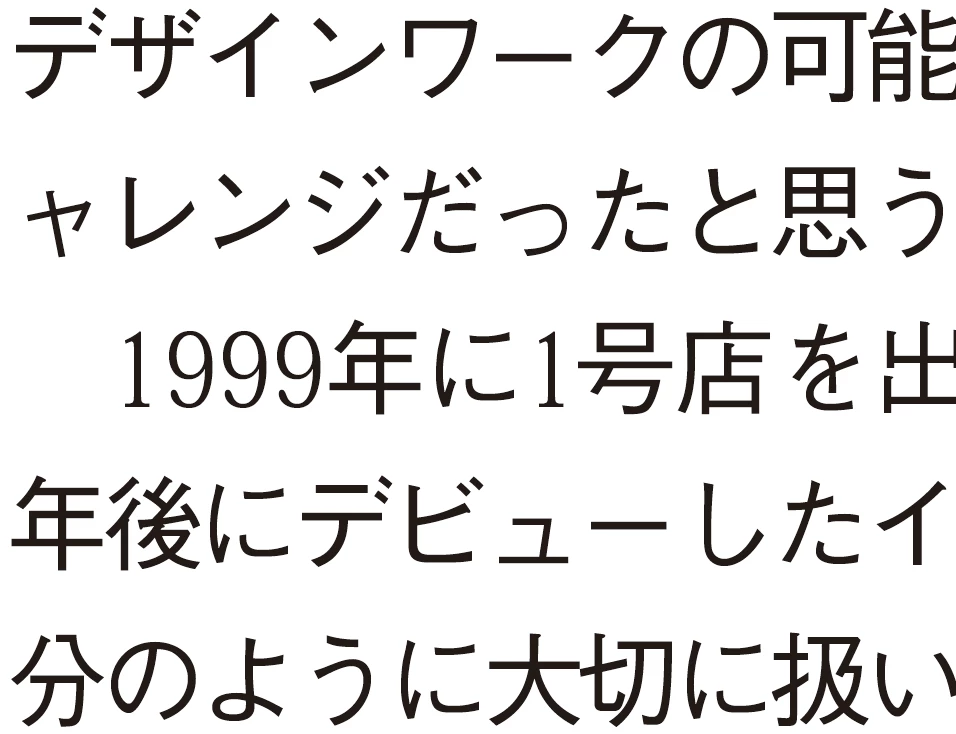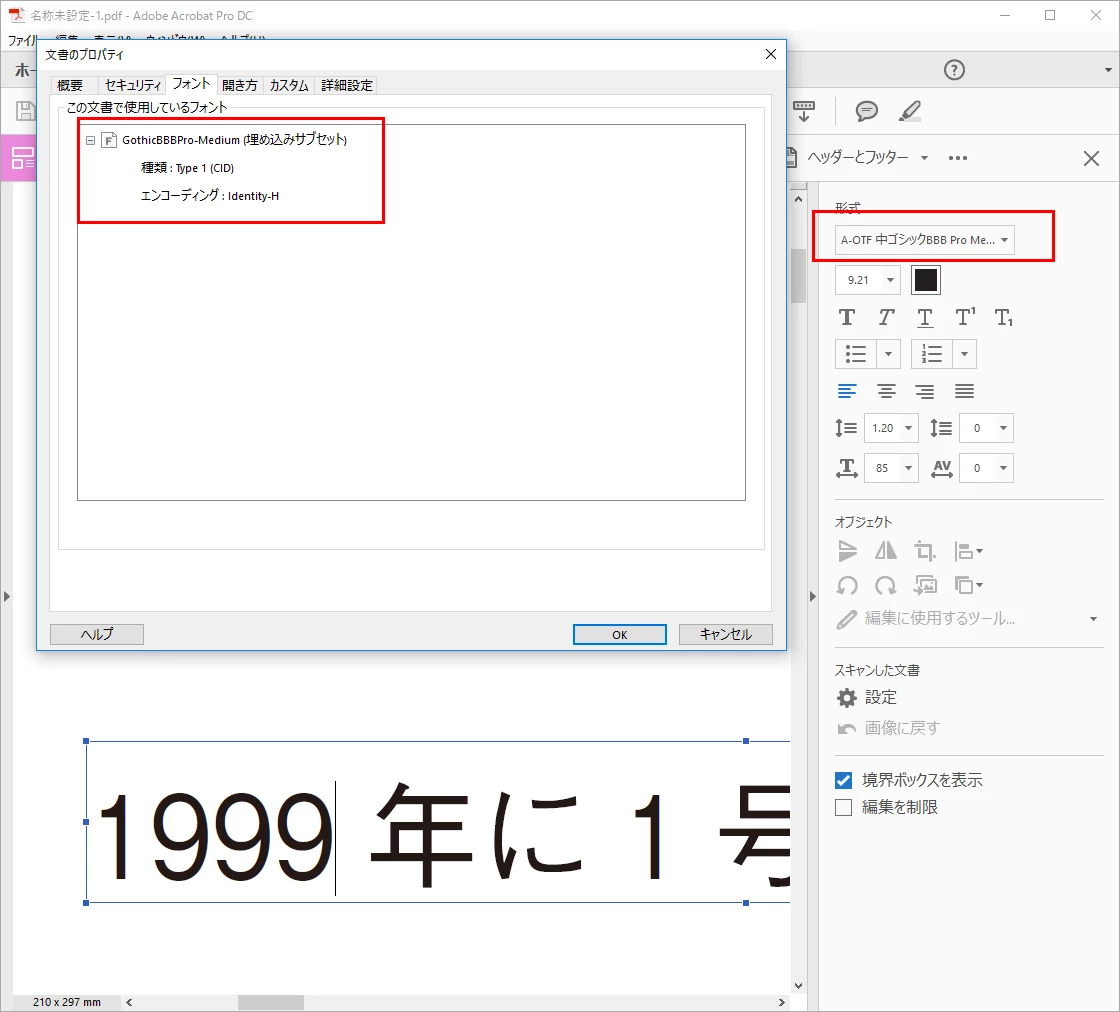
InDesignCS6でPDFを書き出した際に合成フォントが化ける
InDesignCS6(8.0.2)でPDFを書き出した際に合成フォントを使用している箇所で数字の部分だけが文字が化けました。
そういった現象は起きるのでしょうか?
フォントの確認ですが、こちらはAcrobatで行った場合、という話になります。
PDFのプロパティやPDF編集(TouchUp)等で見た場合の、該当部分のフォントはどうでしょうか。
ただ、簡単にですが同様の設定を作って試した限りは再現しませんでした(CS6 8.1)。
また別口の考えなんですが、プロポーショナル字形の85%変形を使う理由がわかりません。
それだけ変形を行うとバランスが悪くなると考えるためです。
もし幅を狭くしたいということであれば、別のコンデンス系欧文フォントを用いるなどであったり、
数字でいえば等幅半角字形を適用するほうが体裁的には望ましいのではないかと思います。
→もう一度PDF書き出しを行ったら正常に書き出されました。
不具合が再現しないということなので、InDesignというよりシステム側の問題かもしれませんね。
例えば、PDFを書きだした時に空きメモリが少なくなっていたとか…。
monokanoさんのアドバイスは有用ですが、
他にも気になる点、確認するべき点は出てきます。
• どのように文字化けしているか
• Acrobatで確認した結果はどうなのか(該当部分のフォント情報)
• PDF作成時のjoboption設定
• 実際に使用しているフォント
• 合成フォントの名称(英数のみになっているかどうか)
• 8.1にアップした場合の結果
• OS環境
記載されたものですと、特に1-2の確認が欠かせませんし、
「化ける」といっても化け方にはさまざまな状態があります。
そこからひとつひとつ紐解いていって、原因を追求・確認する必要が出てきます。
詳細を確認してみました。書ける範囲で書きます。
• どのように文字化けしているか
→全体的にモリサワ書体のA-OTF中ゴシックBBB Proを使用していて半角数字、半角欧文の部分だけ水平比率85%にしています。
• Acrobatで確認した結果はどうなのか(該当部分のフォント情報)
→もう一度PDF書き出しを行ったら正常に書き出されました。
• PDF作成時のjoboption設定
→「高品質印刷」で書き出しています。
• 実際に使用しているフォント
• 合成フォントの名称(英数のみになっているかどうか)
→「A-OTF中ゴシックBBB Pro」
• 8.1にアップした場合の結果
→こちらはできていません
• OS環
→Windows7です。
既知の現象としては下記がありますね。
InDesignからPDFを書き出すとスモールキャップス属性がある文字が化ける|DTPサポート情報
この他にも、PDFにフォントを埋め込みしていないと文字化けすることがあります。
そういった現象は起きるということです。